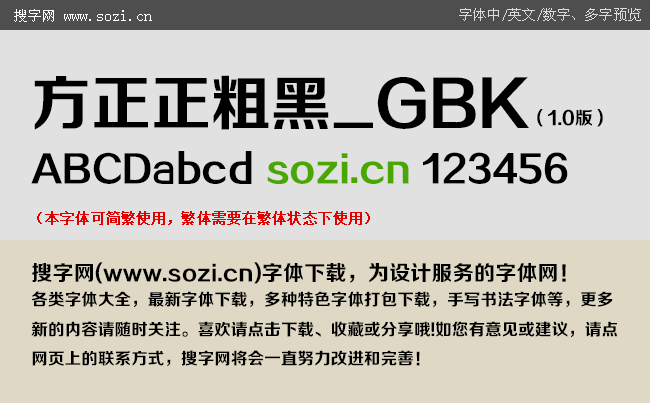
方正正粗黑_GBK
搜字網(wǎng)提供一款方正正粗黑_GBK中文藝術(shù)字體下載,方正正黑系列字體是專為企業(yè)視覺(jué)識(shí)別系統(tǒng)設(shè)計(jì)的專用字體,字體字面擴(kuò)張,重心高,筆畫處理有對(duì)稱的規(guī)律性、鏡像感,效似綜藝。在基礎(chǔ)上結(jié)合黑體筆形及結(jié)構(gòu)特征,使其更富于靈動(dòng)變化,端莊大氣又不失簡(jiǎn)潔時(shí)尚的美感,適用于企業(yè)視覺(jué)識(shí)別系統(tǒng)的設(shè)計(jì)字體,以及版式設(shè)計(jì)中標(biāo)題用字、標(biāo)志設(shè)計(jì)用字等。